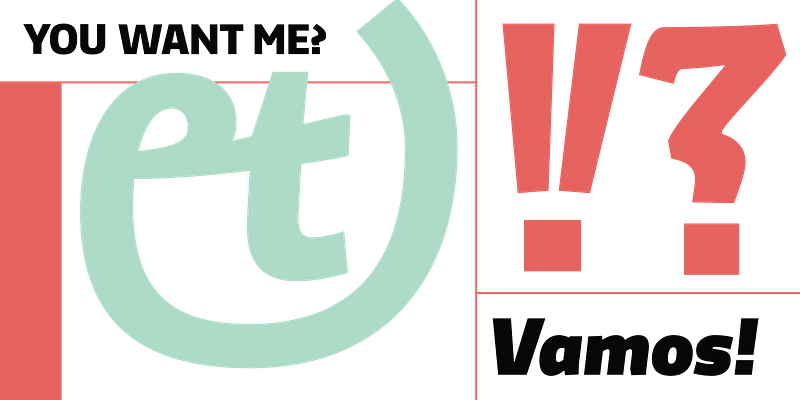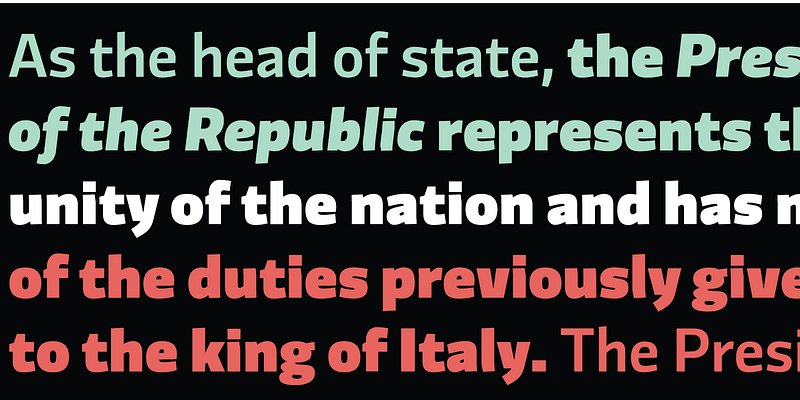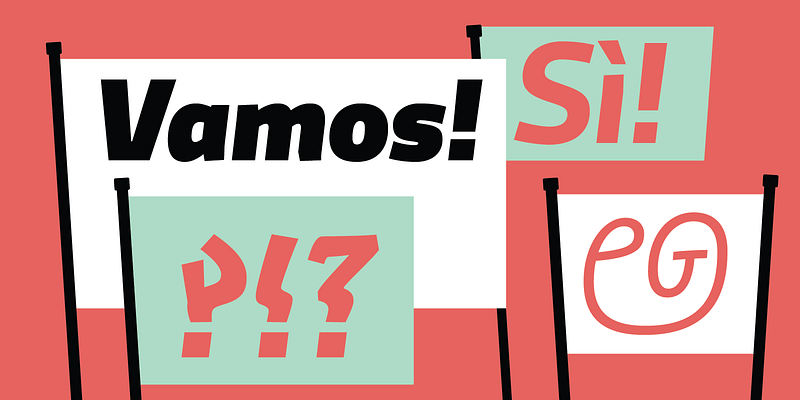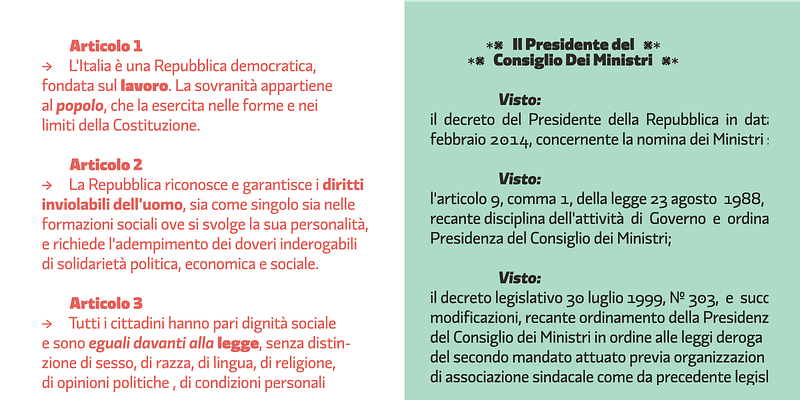
Divenire est une police de qualité organique, avec un style bien à elle. Elle présente des formes de lettres carrées, des terminaisons horizontales, des jonctions angulaires et des variations de largeurs de tige.